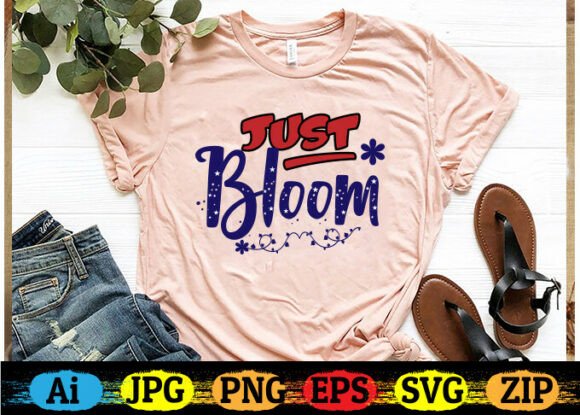
Just Bloom Free T-shirt Designs
Mencari elemen reka bentuk yang sesuai boleh menjadi mencabar, tetapi Just Bloom Free T-shirt Designs menawarkan koleksi luar biasa yang menaik taraf karya anda serta-merta.
Dicipta dengan ketepatan, Just Bloom Free T-shirt Designs menyediakan vektor yang bersih, tipografi yang licin dan lesen komersial untuk ketenangan fikiran.